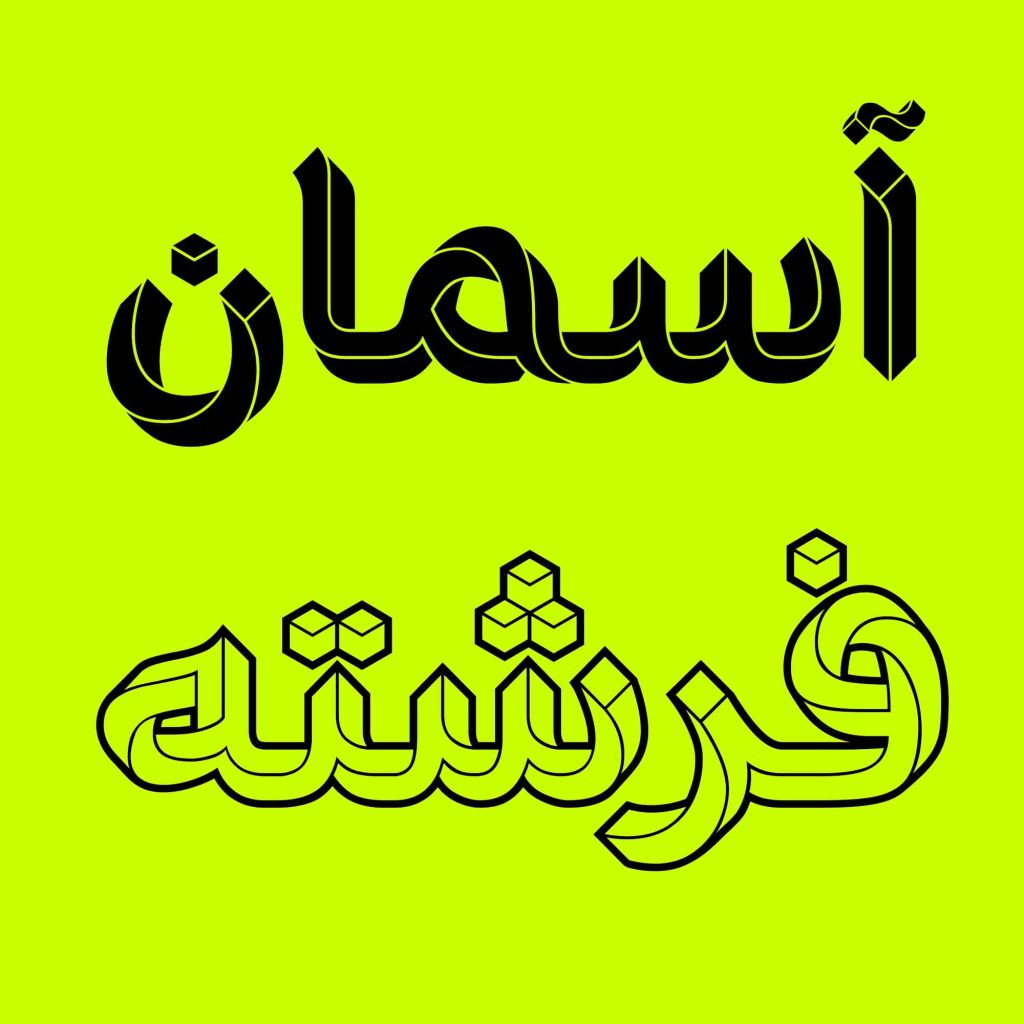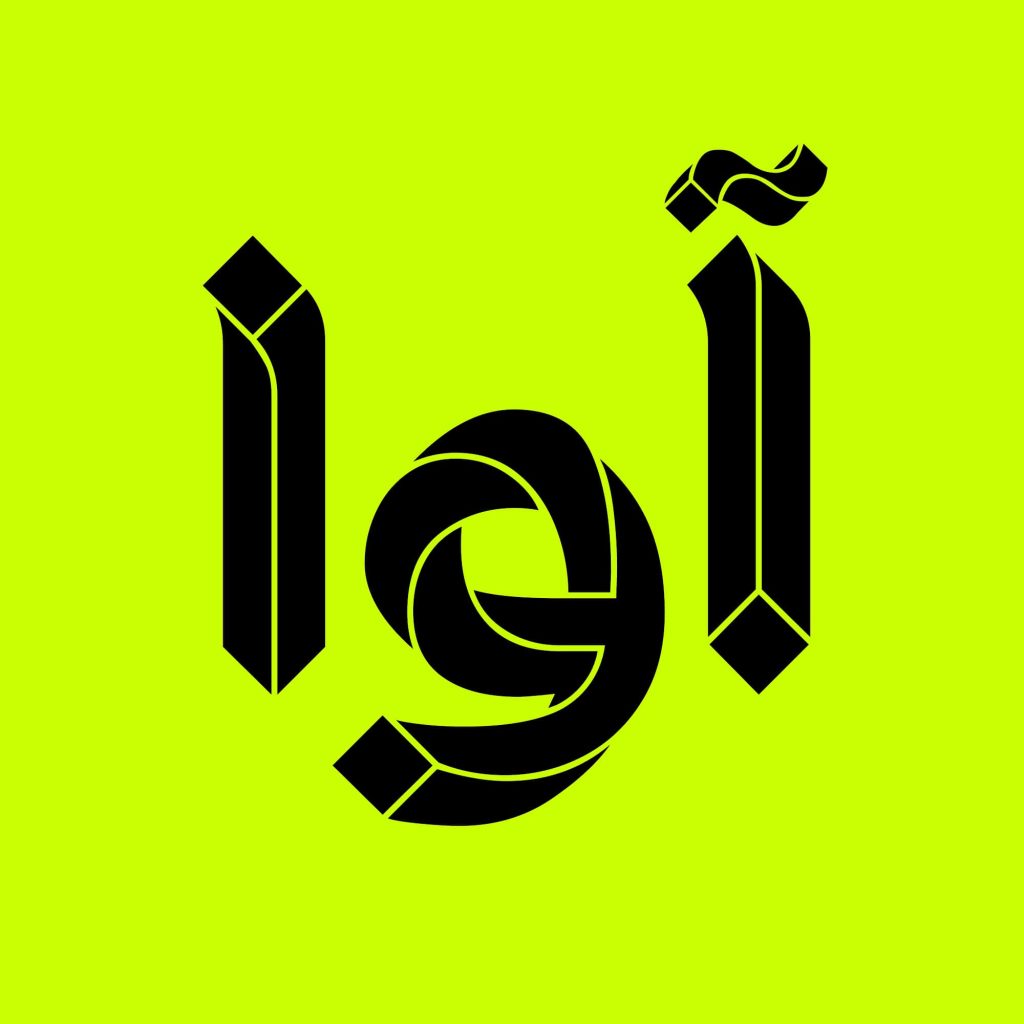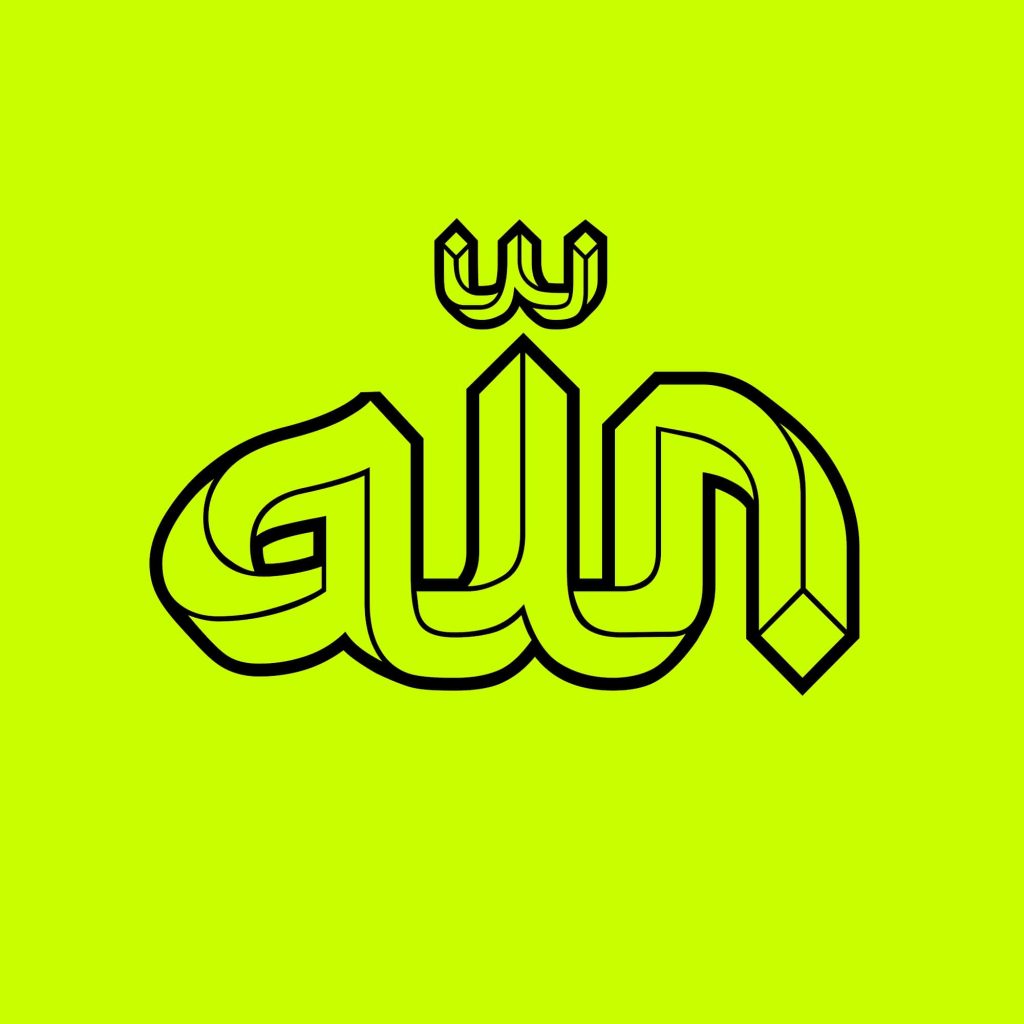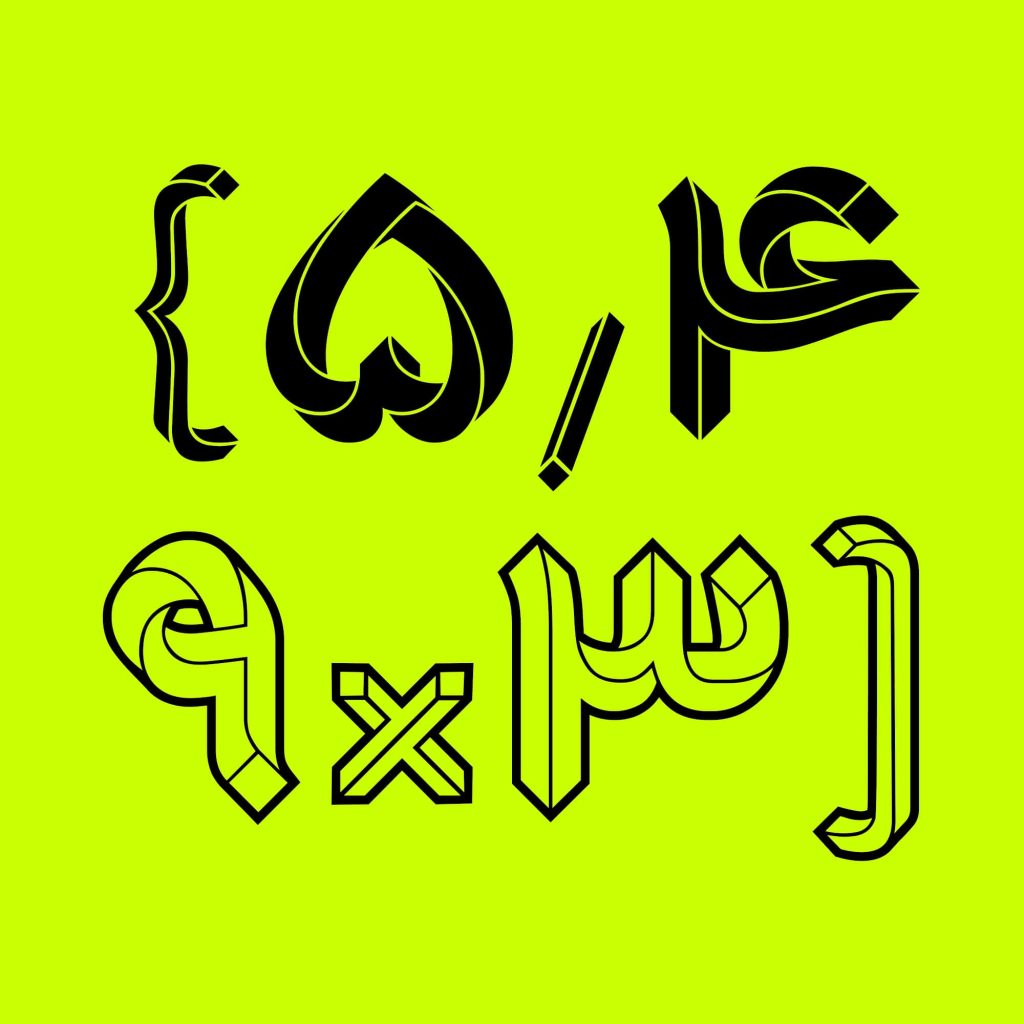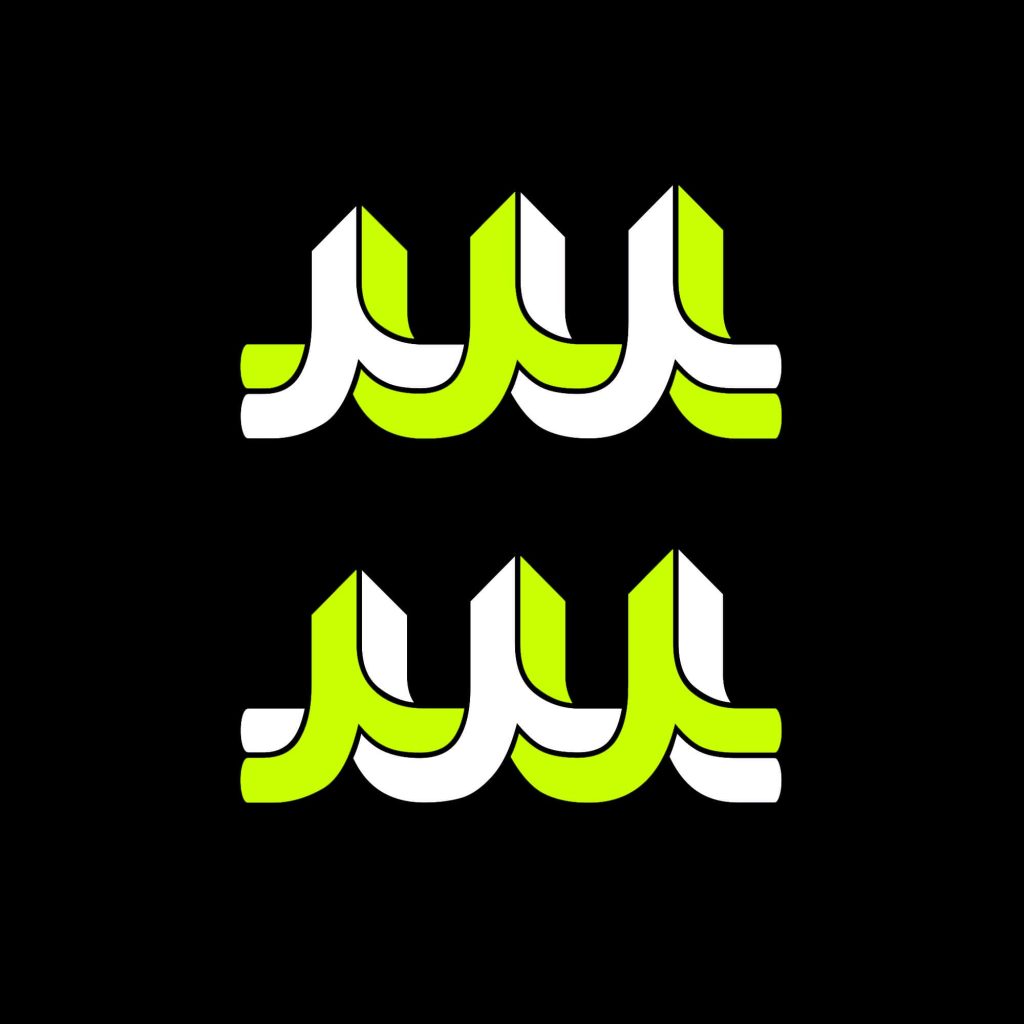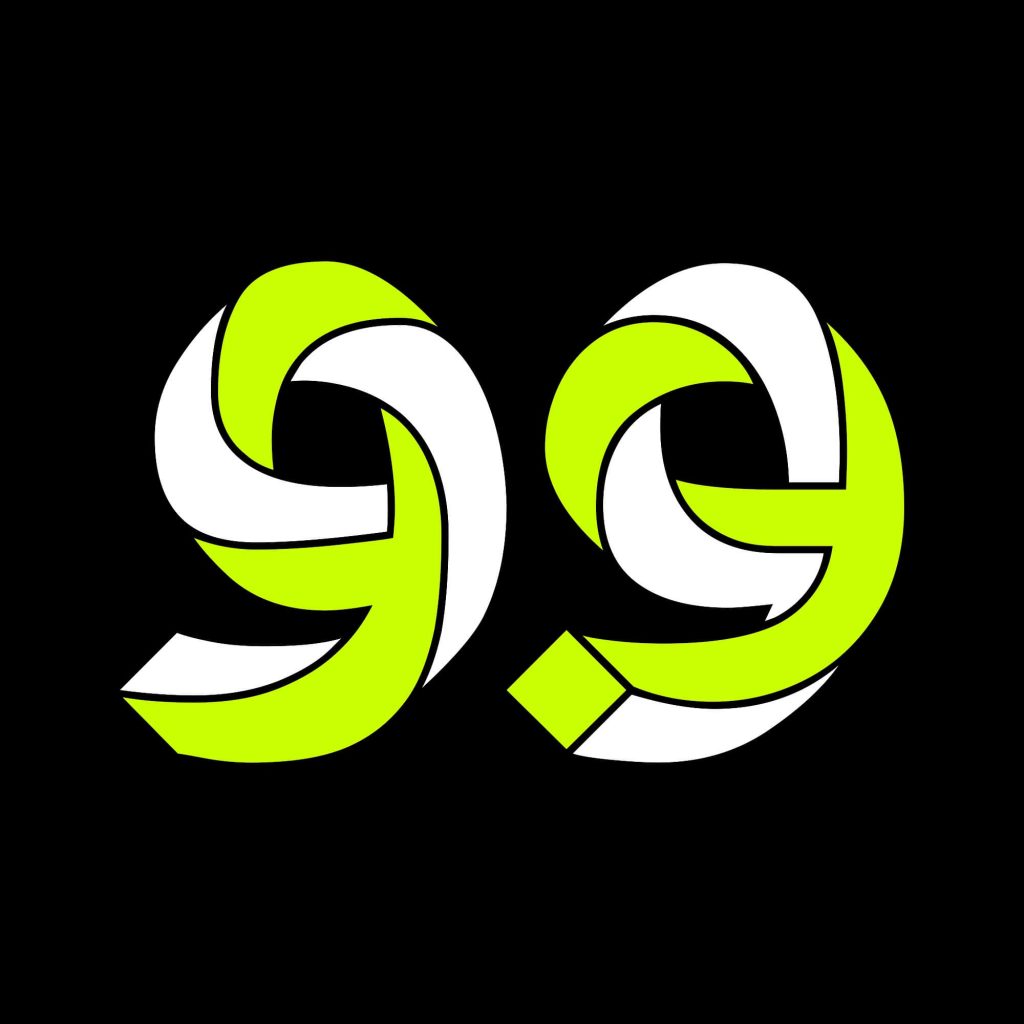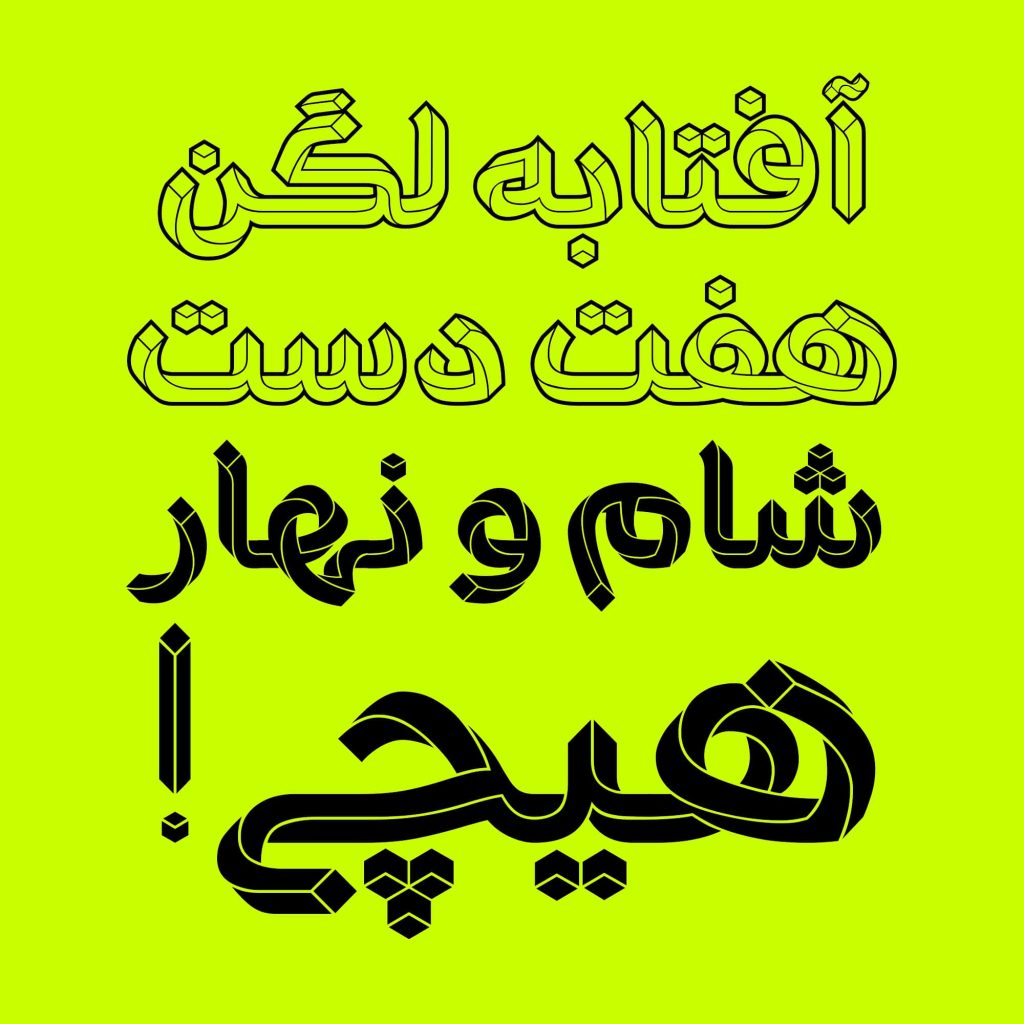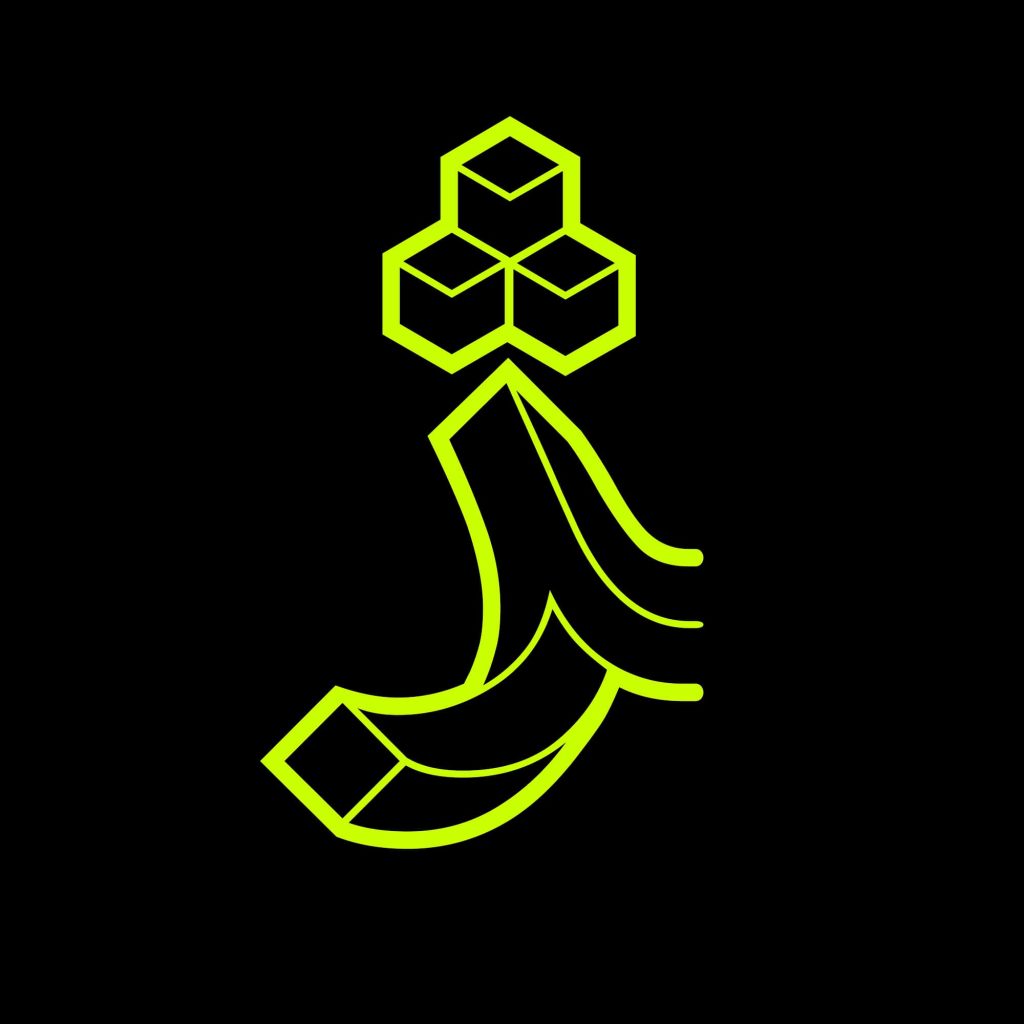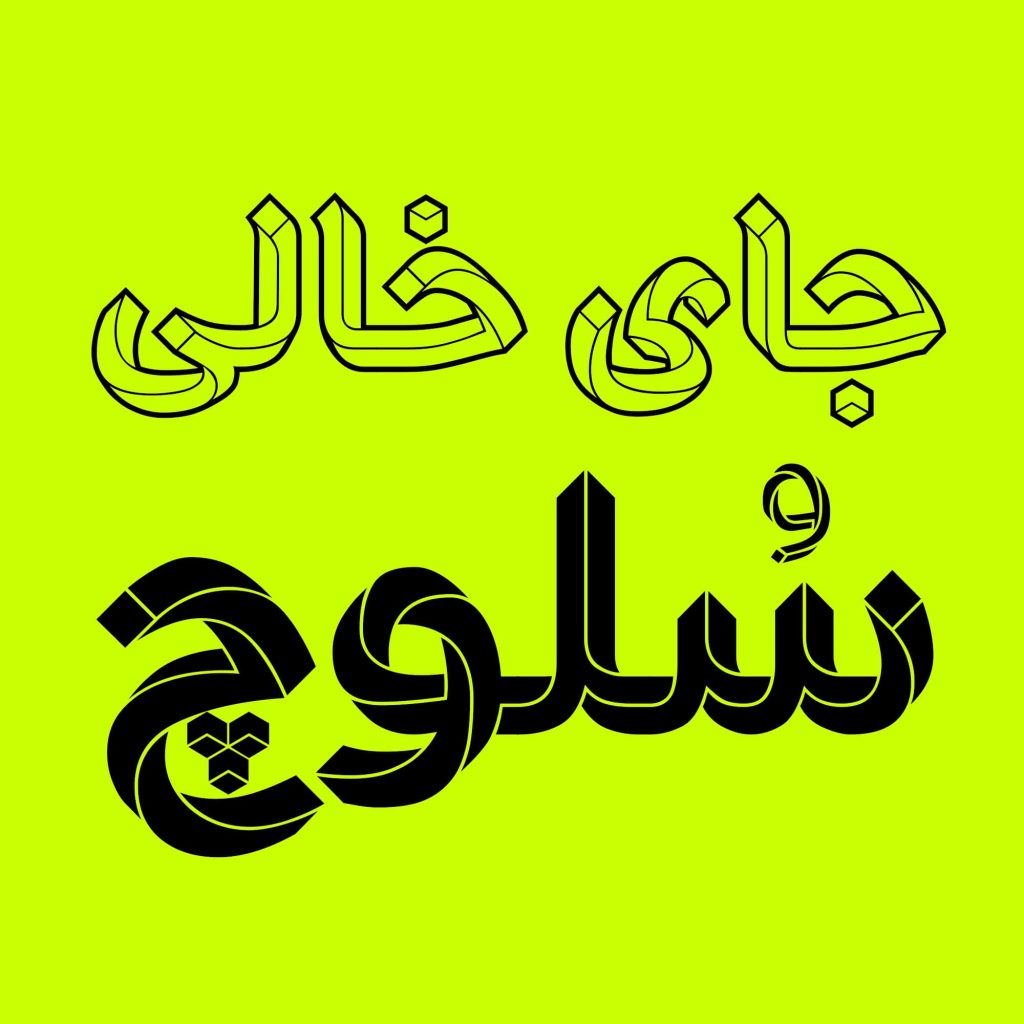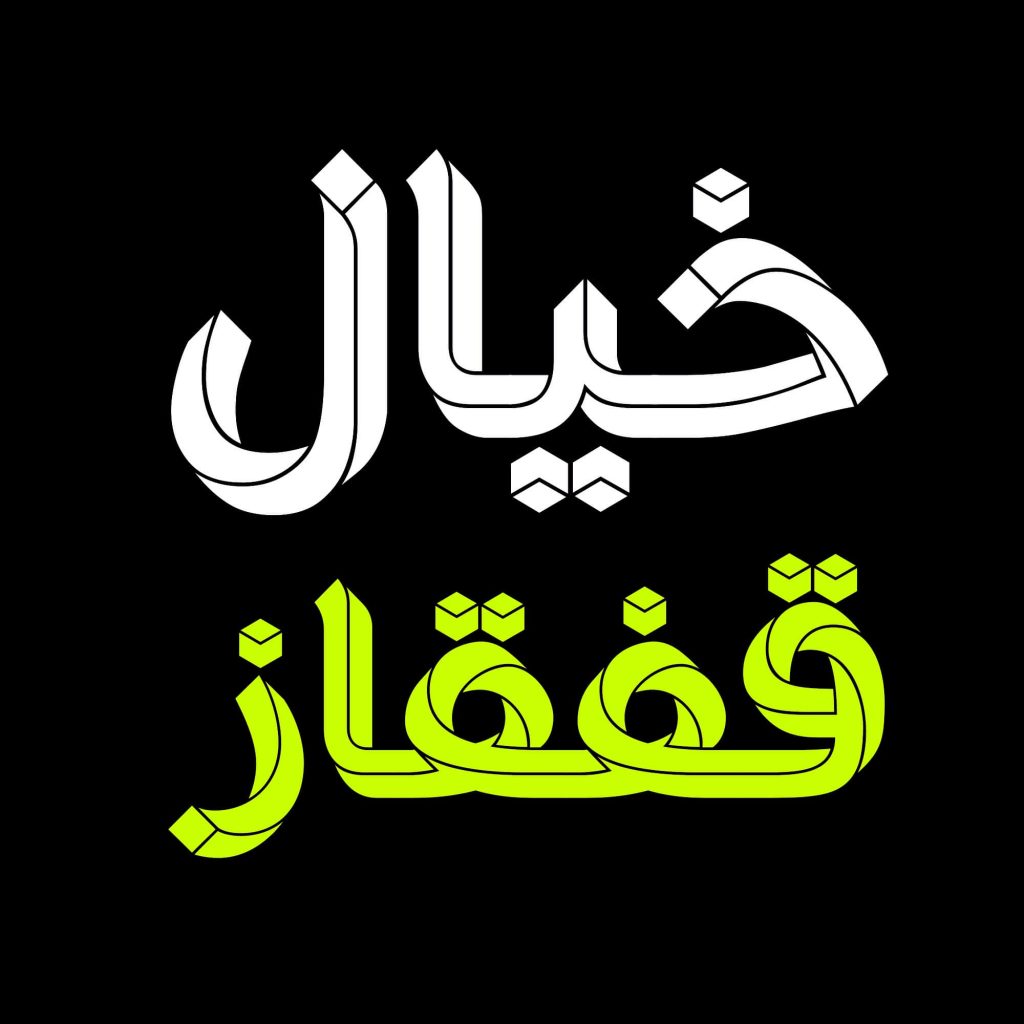
فونت پارادوکس قلمی با ویژگی نمایشی اقتباس گرفته از آثار موریس اشر می باشد. این تایپ فیس در نوع طراحی خود بسیار خاص و ویژه می باشد که نگاه مخاطبین را به خود جذب می کند.
فونت پارادوکس – قلمی با طراحی خاص و ویژه
فونت پارادوکس تایپ فیسی که ظاهری منحصر به فرد در مقایسه با دیگر قلم های فارسی دارد. پارادوکس در نگاه ابتدایی 3 بعدی به نظر می آید ولی با اندکی دقت می توان دریافت که محصول ترکیب شده از دو طراحی است. البته فرم های حروف آن در نهایت دقت و ظرافت طراحی شده اند تا خروجی و برآیند کار اینچنین زیبا و دقیق انجام شده و طرحی 3 بعدی را رقم زند.
اگر بخواهیم قلمی مشابه پارادوکس به شما معرفی کنیم مطمئنا فرم 3 بعدی آن انحصار به خود این قلم است و یافت نشدنی است اما از نظر هم خانوادگی و نزدیکی فرم های طراحی فونت باوان هم از سبک و سیاق پارادوکس است . جوان است و پرانرژی و مناسب طراحی فضاهای جدید و و امروزی.
پارادوکس قلمی نمایشی مناسب عناوین تبلیغاتی
ویژگی اصلی این تایپ فیس نمایش بودن آن است ساخته و طراحی شده تا نگاه ها را به خود جذب کند . از همین رو مناسب برای متون کوتاه و عناوین است . دارای روحیه ای محکم و جوان است و برای تیتر های تبلیغاتی انواع محصولاتی است که می‌خواهند پویایی و خاص بودن خود را به نمایش بگذارند بسیار مناسب و اثر گذار است..
می توان در کاربرد هایی نظیر انواع تبلیغات، پست و استوری و بسته بندی محصولات غذایی، اسباب بازی، پوشاک، ورزشی و … از آن بهره مند شد چرا که نمایشی و هیجان انگیز و رباینده نگاه ها به دلیل فرم طراحی خاص و منحصر به فرد خود است
عباس ابراهیمی طراح پارادوکس، شاکله و اسکلت این تایپ فیس را بر اساس آثار موریس اشر، الهام و اقتباس گرفته است. با کمک جستجو و آزمون و خطا و تلاش در ارائه سبکی جدید و منحصر به فرد این قلم را به عرصه تایپوگرافی فارسی رسانیده است.
وی در این باره می افزاید که “در سال ۹۸، با تمرکز جدی‌تر به طراحی فونت پرداختم و نهایتاً تا پایان همان سال، طراحی و اجرای نرم‌افزاری آن تقریباً تمام شد. در سال ۱۴۰۱، با راهنمایی دقیق و موثر دوست خوبم، امین عابدی (برای کد نویسی) نهایتاً این اثر آماده انتشار شد “.